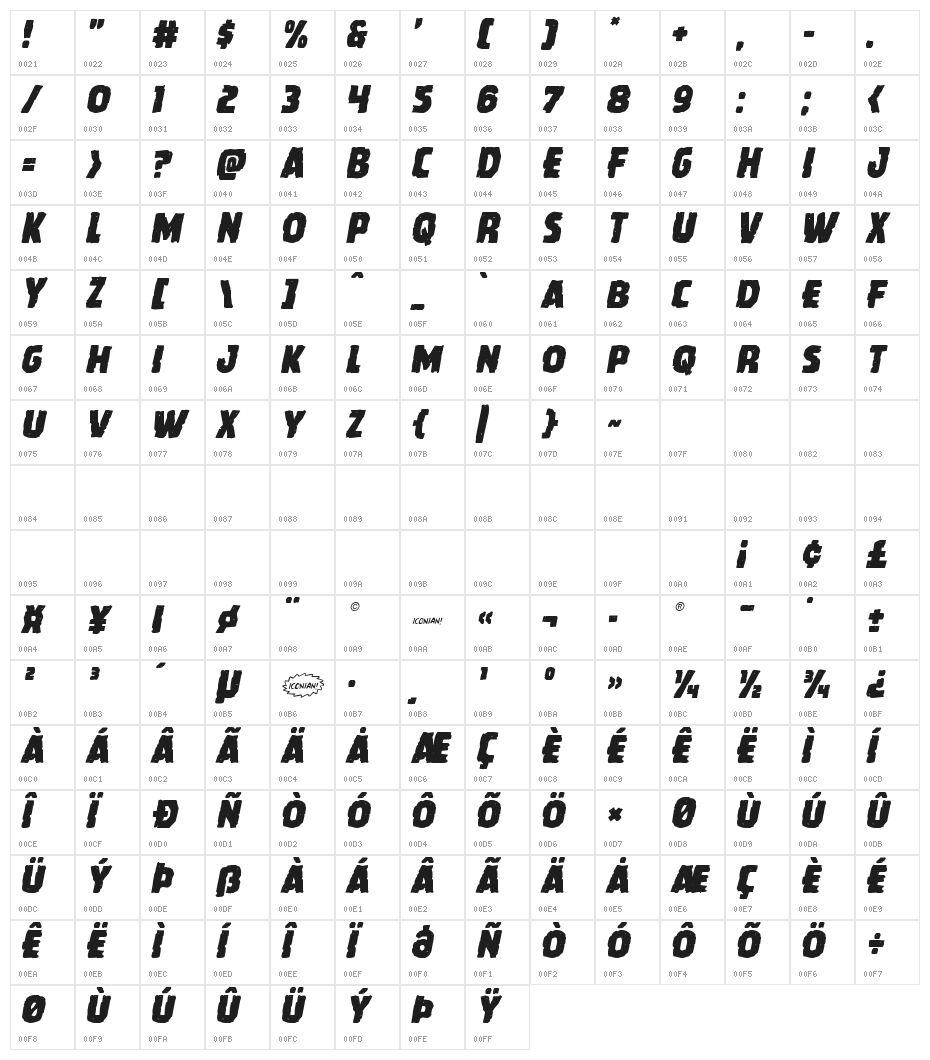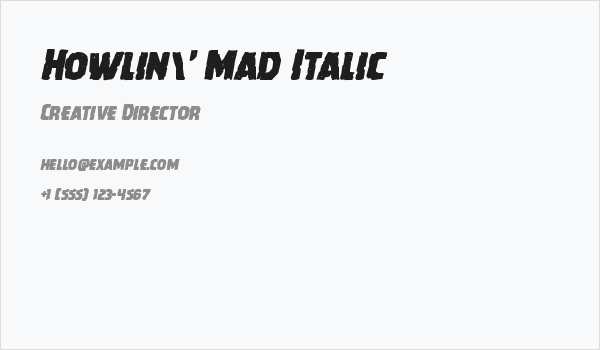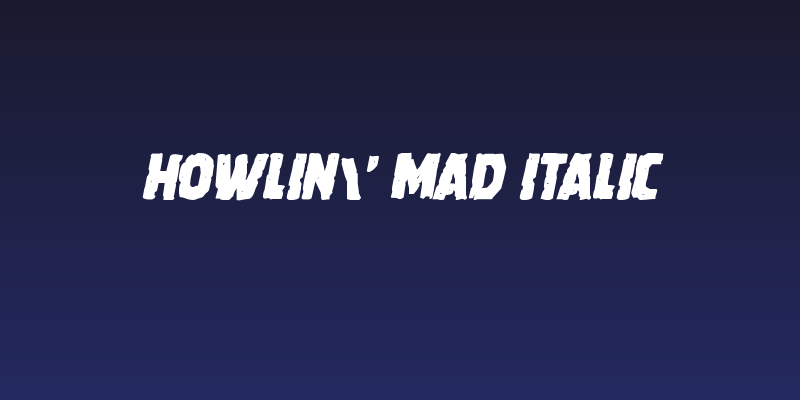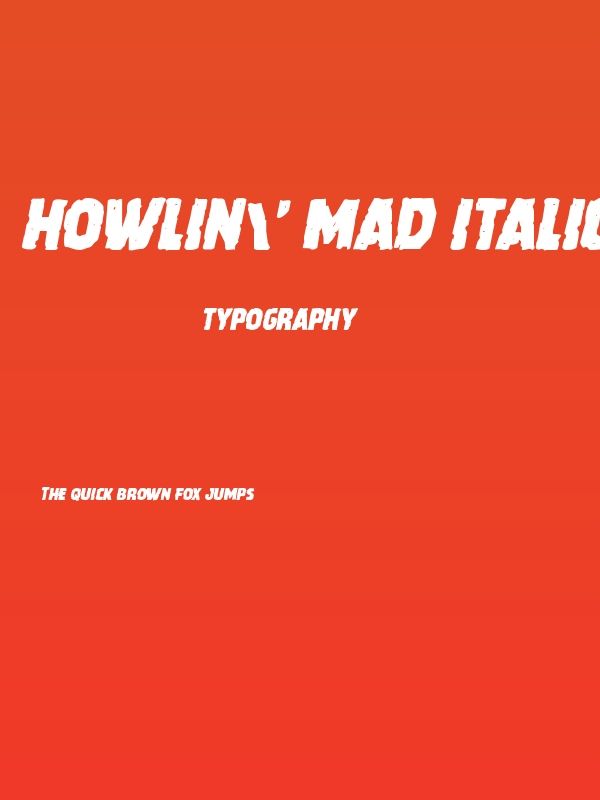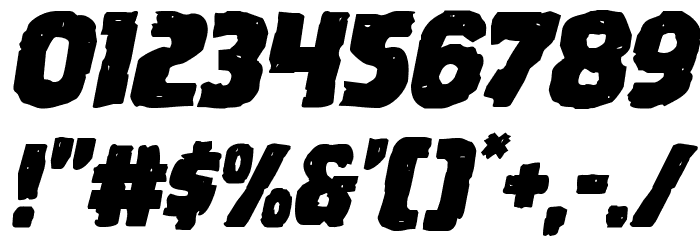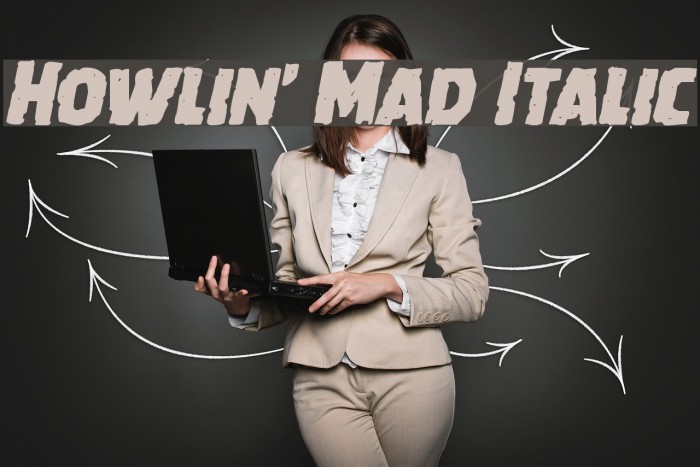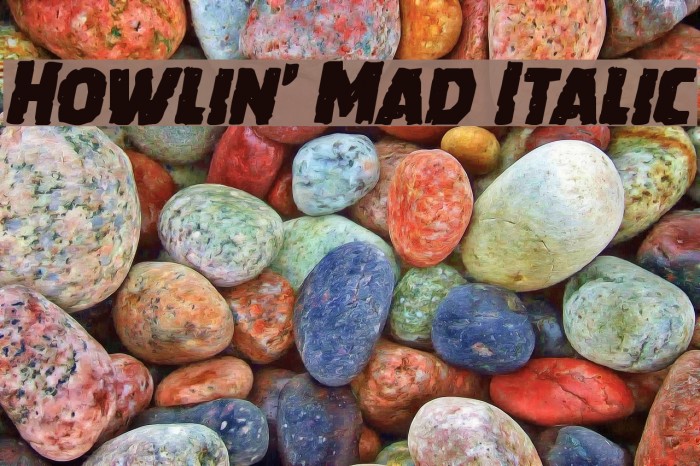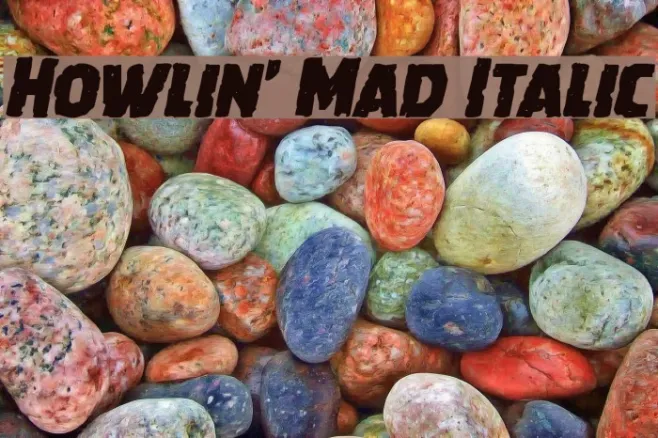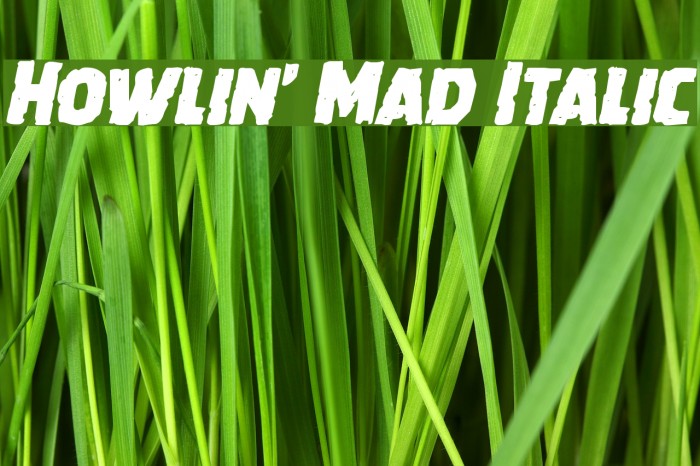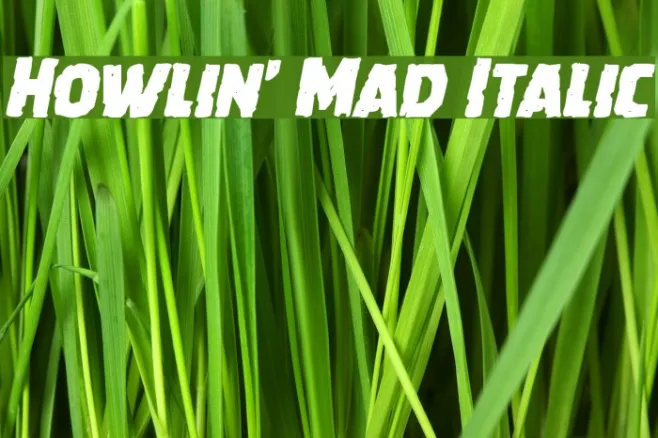
Howlin' Mad Italic Font
| Vorgeschlagene Projekte | Ideal for posters, album covers, video game graphics, and branding that requires a bold, edgy look. |